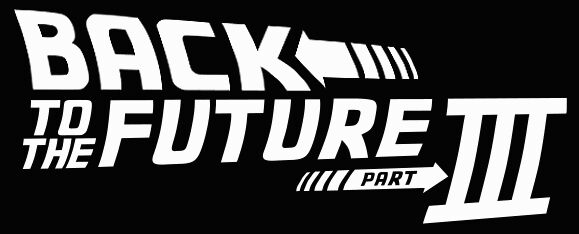
خط Back to the future font من تصميم Cyril B. هو خط عرض مجاني ينقل تصميمك فوراً إلى عالم الخيال العلمي المتوهج في الثمانينات. الحروف الطويلة والضيقة تميل للأمام وكأنها في منتصف قفزة نحو سرعة الضوء، مع ضربات عريضة وزوايا حادة تمنح طابعاً صاخباً وسريعاً بلمسة نيون. التباعد الضيق يجعل الكلمات مدمجة وقوية، بحيث يبرز حتى العنوان القصير كشعار جريء فوق خلفية داكنة مرصعة بالنجوم أو تدرج لوني كلاسيكي.
باستخدام Back to the future font، ستتألق العناوين في ملصقات الأفلام، وفنون المعجبين، وصور مصغرة لـ YouTube، وأغلفة الألعاب، ومنشورات الفعاليات، والمنتجات التذكارية. هذا الخط المجاني يتألق عند استخدامه بأحجام كبيرة لمنحه مساحة للتنفس، مع دعمه بخط بلا زوائد (sans serif) نظيف ومحايد للنص الأساسي. أضف تداخلات لونية زاهية أو تأثيرات الكروم، وستبدو عناوينك وكأنها جاهزة للانطلاق عبر آلة الزمن.